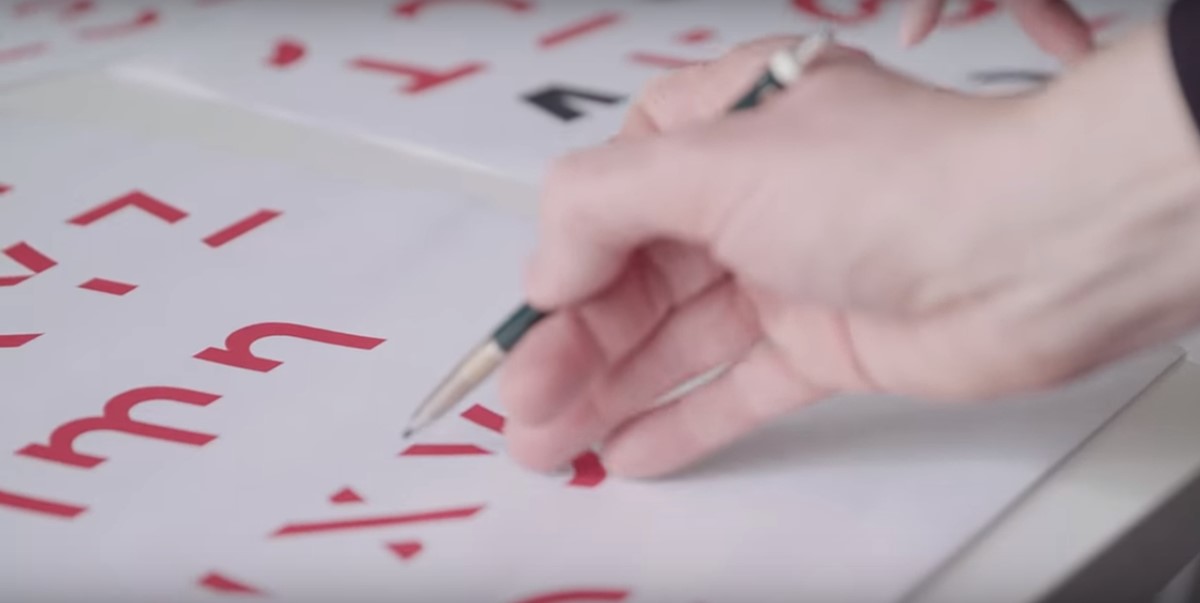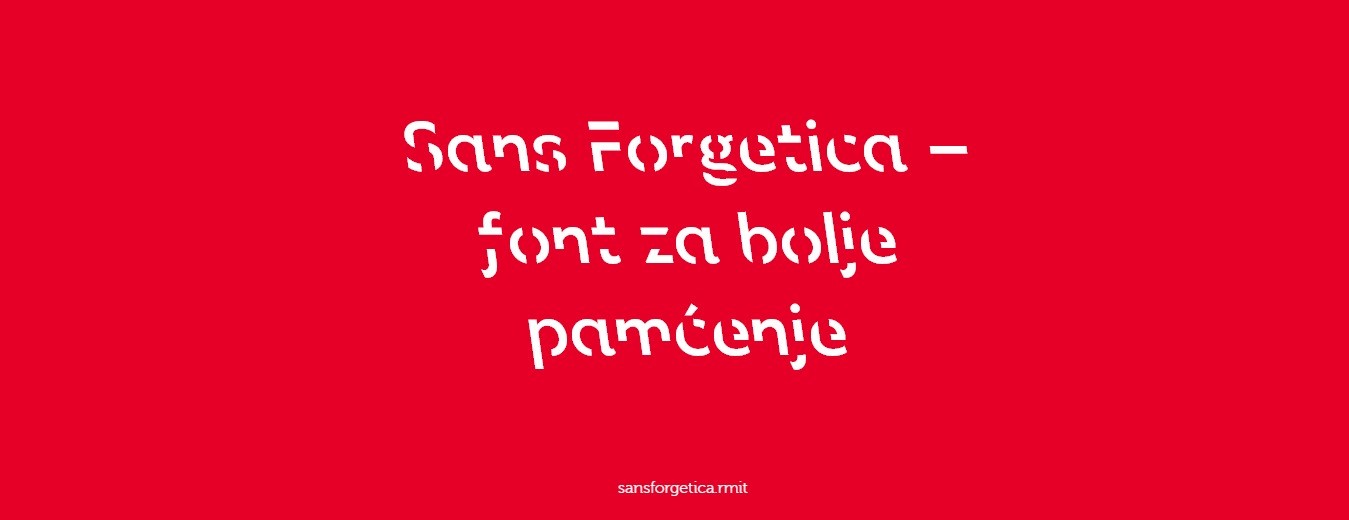
Sans Forgetica – font za bolje pamćenje
Australski znanstvenici razvili su računalni font koji je namjerno učinjen teškim za čitanje, što bi trebalo poboljšati pamćenje pročitanoga
Različiti tipografski oblici slova, odnosno fontovi, najčešće se koriste za dekoriranje teksta, isticanje njegovih pojedinih dijelova i uklapanje u određene stilove, no ponekad se specijalizirani fontovi izrađuju s namjerom da pomognu ljudima, primjerice, u borbi protiv disleksije. Znanstvenici sa sveučilišta RMIT u Melbourneu predstavili su svoju ideju za koju misle da bi mogla pomoći mnogima – font koji olakšava pamćenje pročitanoga.
Sans Forgetica, kako je ironično nazvan, namjerno je izrađen kako bi ga se teže čitalo. Slova su neprirodno nagnuta ulijevo, a iz svakoga od njih uklonjen je jedan dio, pa mozak čitatelja mora "raditi prekovremeno" kako bi dešifrirao ono što je ovim fontom napisano. I to, kažu znanstvenici (a potvrđuje i njihova studija), omogućava da čitatelj bolje zapamti tekst pisan ovim fontom nego nekim običnim poput Ariala.
Poboljšanje pamćenja, doduše, nije veliko. Kod 400 ispitanika udio zapamćenog teksta popeo se s 50 na 57% kad je font Arial zamijenjen Sans Forgeticom. Budući da je istinski teško čitati duže tekstove otisnute ovim fontom, njegovi autori preporučuju da se njime ispisuju kraći dijelovi teksta koje želimo da čitatelj upamti.